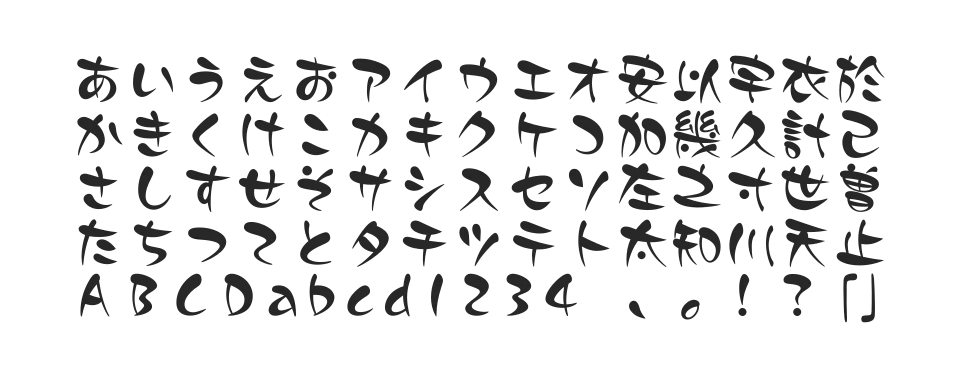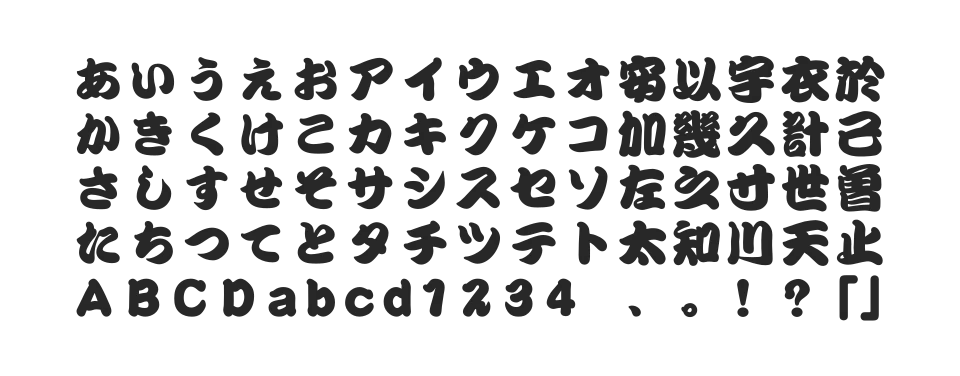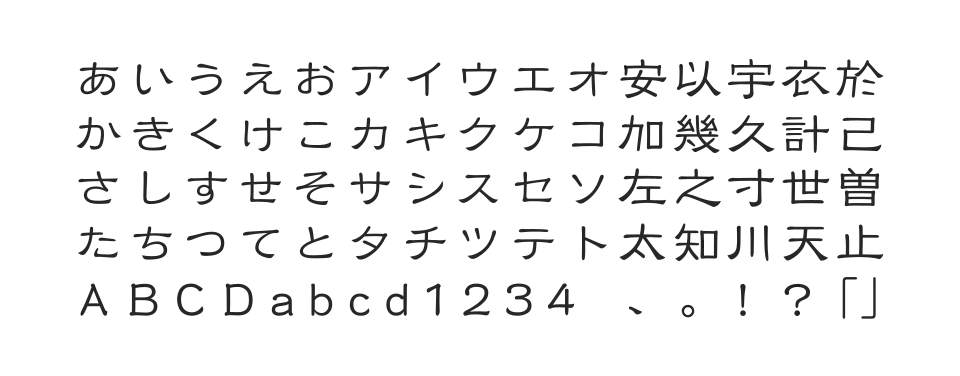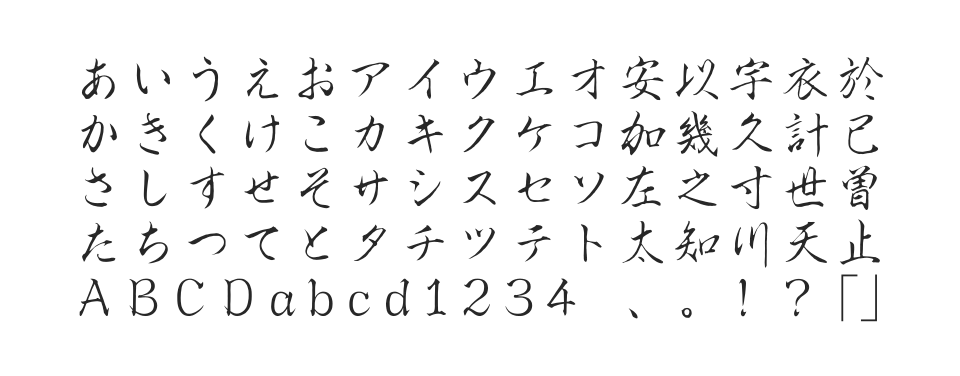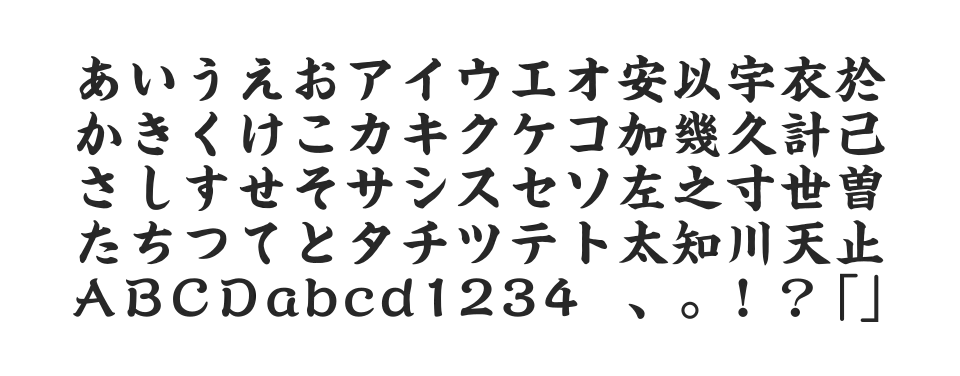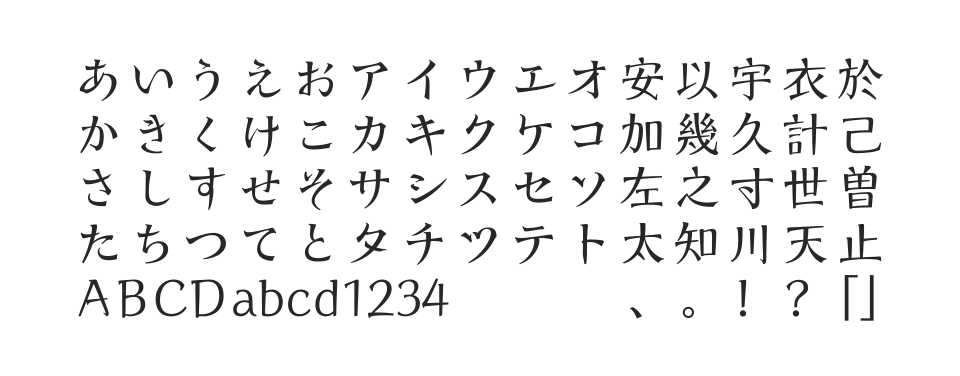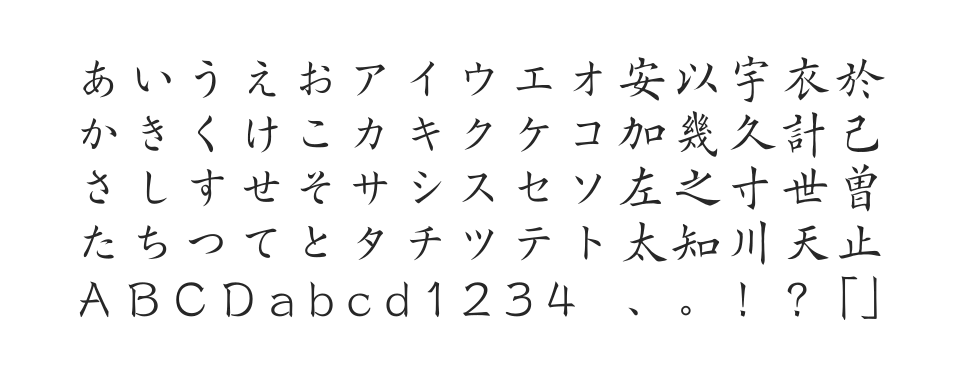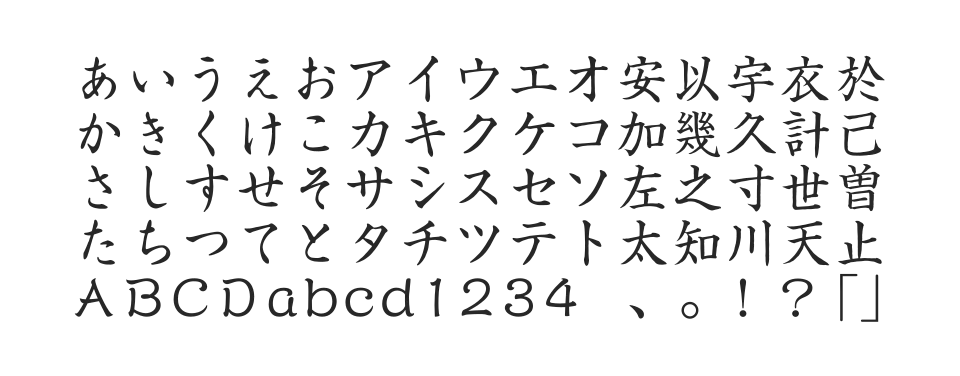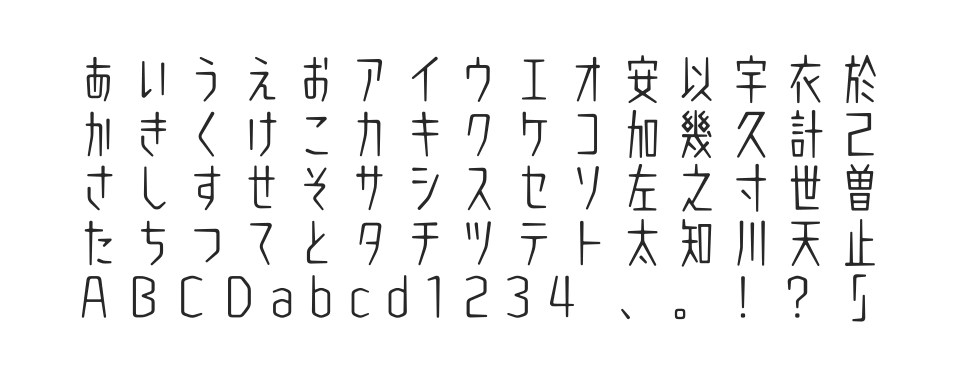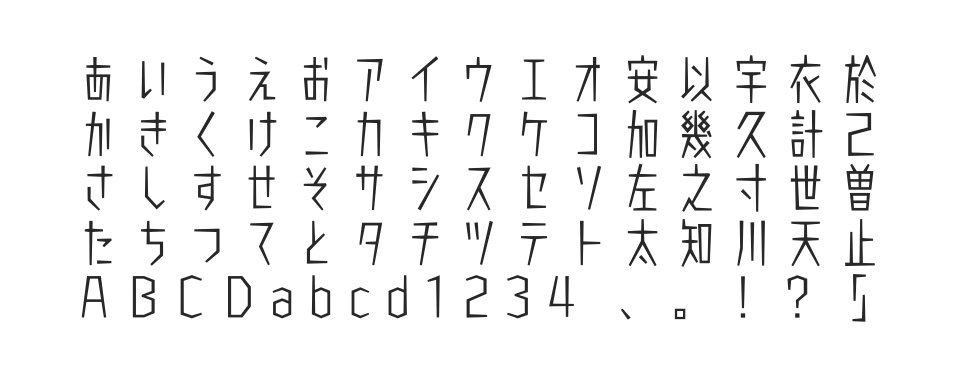
直線で構成されたシンプルな設計でありつつ独特の印象を与える書体です。ウエイトごとに異なる字幅が特徴で、ゲームやコミックなどコンテンツの世界観を演出するシーンで使いやすいフォントです。
直線のみで構成されたシンプルな設計のラピスエッジを元に開発された丸ゴシック系のデザイン書体です。ラピスエッジのコンセプトを踏襲しつつ先端を丸く処理したモダンなフォントです。
筆文字のもつ力強さや重厚感を大切にしながら、漢字・かなの大きさをできるだけ揃えることで、字並びの美しさと使いやすさを追求した楷書体です。人間味を感じさせる丁寧な筆使いが特長です。
中国の唐の時代に楷書の名筆として知られた欧陽詢の書に倣い、その特徴である端麗な風姿をよみがえらせた楷書体です。颯爽とした高い品格と威厳を感じさせる美しい文字組みを実現します。
特徴ある自由なエレメントをもったオリジナル書体で、明朝体に近いコントラストを持ちながら親しみやすい印象を与えます。強さとやわらかさをあわせ持つオリジナリティのあるスタイルです。
従来の楷書のイメージとは一線を画す極太の楷書体で、どっしりと力強い筆づかいが独特の存在感を放ちます。キャッチコピーや見出し、ディスプレイなどに威力を発揮する楷書体です。
くずしを控えめにした読みやすい行書体で、筆のなめらかな流れの中に程よい強弱があり、小気味のよい筆づかいが特長です。和文デザインに優雅さと親しみやすさを添えます。
書道の美しさを活かした隷書体で、古典的な書風を現代に蘇らせた格調高いフォントです。日本語の美しい表現に最適な書体として多くのデザイナーに愛用されています。
歌舞伎の外題や看板用の伝統的書体。太くうねりのある運筆で威勢のいい江戸歌舞伎の感性を表現。演劇や催事のタイトルに最適。
カジュアル感覚の筆文字書体。水彩平筆風の線とポップな雰囲気で、自由でファッショナブルな表現に適している。インパクトあるデザイン。